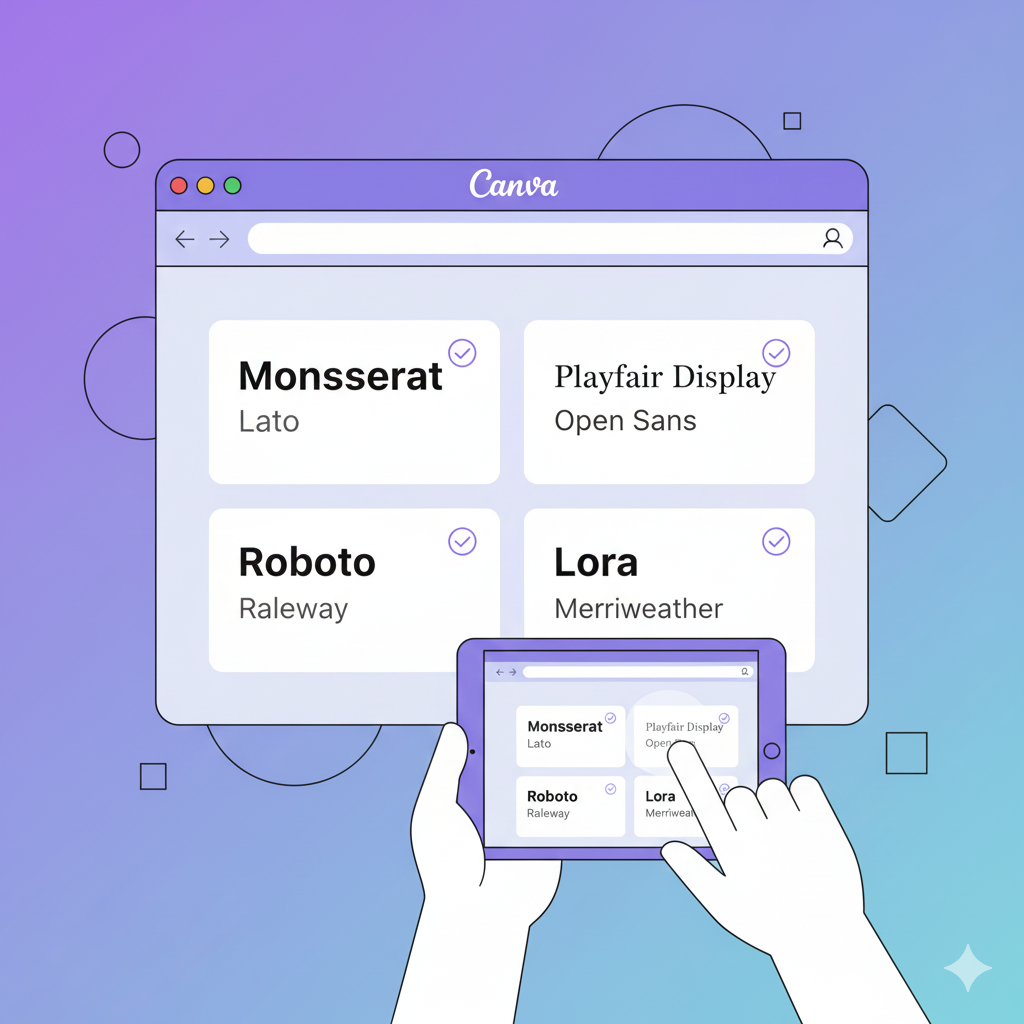
Gubuku – Font memiliki peran besar dalam branding karena secara visual bisa menyampaikan emosi dan karakter bisnis. Misalnya, font tebal dan modern seperti Montserrat memberi kesan profesional dan percaya diri, sedangkan font bergaya tulisan tangan seperti Playlist Script menciptakan kesan personal dan hangat.
Menurut Canva Design School (2024), pemilihan kombinasi font yang baik dapat meningkatkan keterbacaan hingga 40% dan membuat desain tampak lebih harmonis. Kombinasi yang tepat juga membantu audiens mengenali merek hanya dari gaya tulisan yang digunakan.
Jadi, sebelum memilih, pastikan kamu tahu karakter bisnismu: apakah formal, kreatif, ramah, atau elegan? Ini akan membantu menentukan kombinasi font yang paling sesuai.
Prinsip Dasar Mengombinasikan Font di Canva
Sebelum masuk ke contoh kombinasi font, pahami dulu prinsip dasar dalam mengombinasikan font agar hasil desainmu seimbang:
Gunakan maksimal dua jenis font.
Terlalu banyak jenis huruf membuat desain terlihat berantakan. Cukup pilih satu untuk judul dan satu untuk isi teks. -
Kontraskan gaya font.
Kombinasi yang menarik biasanya memiliki perbedaan yang jelas, misalnya antara serif dan sans-serif, atau antara font formal dan kasual. -
Pastikan keterbacaan tetap tinggi.
Walaupun estetika penting, kejelasan teks tetap prioritas utama—terutama untuk materi promosi seperti poster, brosur, atau konten media sosial. -
Sesuaikan dengan identitas brand.
Jika bisnismu bergerak di bidang kreatif, font yang lebih bebas bisa digunakan. Tapi untuk bisnis profesional seperti konsultan atau hukum, font yang bersih dan elegan lebih cocok.
Kombinasi Font Populer Canva untuk Bisnis Profesional
Jika kamu menjalankan bisnis yang ingin terlihat modern, tepercaya, dan profesional, kombinasi berikut bisa menjadi pilihan:
1. Montserrat + Open Sans
Montserrat cocok untuk judul karena tampilannya tegas dan modern.
Open Sans digunakan untuk isi teks karena mudah dibaca di berbagai ukuran layar.
Kombinasi ini banyak digunakan oleh startup teknologi, konsultan bisnis, hingga agensi digital.
2. Lora + Roboto
Lora memiliki sentuhan klasik berkat gaya serif-nya, ideal untuk merek yang ingin tampil elegan tapi tetap modern.
Roboto yang bersih dan minimalis sangat cocok untuk teks pendukung.
Menurut Font Pair (2023), pasangan ini sering dipakai dalam presentasi dan website profesional.
3. Playfair Display + Poppins
Playfair Display menghadirkan nuansa mewah dan feminin.
Poppins memberi keseimbangan dengan bentuk huruf yang bulat dan tegas.
Kombinasi ini cocok untuk bisnis fashion, kosmetik, atau brand personal yang elegan.
Kombinasi Font Canva untuk Bisnis Kreatif dan Online Shop
Bisnis kreatif seperti toko online, usaha handmade, atau brand fashion memerlukan tampilan yang lebih ekspresif. Canva menyediakan banyak font yang bisa mencerminkan karakter unik bisnismu.
1. Raleway + Pacifico
Raleway tampak bersih dan elegan, cocok untuk teks utama.
Pacifico, dengan gaya tulisan tangan yang santai, cocok untuk logo atau headline.
Kombinasi ini menciptakan kesan ramah dan kreatif, sering dipakai oleh brand kuliner dan toko pakaian online.
2. Bebas Neue + Lato
Bebas Neue kuat dan berani, sangat menonjol untuk judul.
Lato lembut dan profesional, menjaga keseimbangan dalam isi teks.
Kombinasi ini populer di dunia desain promosi dan iklan digital (sumber: Canva Fonts Library, 2024).
3. Amatic SC + Josefin Sans
Amatic SC punya karakter unik dan cocok untuk desain yang ingin tampak “handmade”.
Josefin Sans memberi kesan modern agar desain tetap terstruktur.
Ideal untuk bisnis craft, kafe, atau produk rumahan.
Kombinasi Font Canva untuk Bisnis Ramah Alam dan Kesehatan
Bisnis di bidang kesehatan, wellness, atau produk alami membutuhkan kombinasi font yang terlihat tenang, bersih, dan natural.
1. Nunito + Lora
Nunito memiliki bentuk huruf yang lembut dan nyaman dibaca.
Lora menambah sentuhan klasik dan elegan.
Kombinasi ini cocok untuk brand skincare alami atau produk herbal.
2. Quicksand + Playfair Display
Quicksand ringan dan modern, membuat desain terlihat ramah.
Playfair Display memberi kesan elegan pada bagian judul.
Kombinasi ini populer di situs wellness dan yoga (sumber: Canva Community Forum, 2024).
3. Poppins + Raleway
Dua font sans-serif ini terlihat bersih dan rapi, ideal untuk bisnis yang mengedepankan profesionalisme dan minimalisme.
Kombinasi Font Canva untuk Branding dan Logo Bisnis
Jika kamu ingin membuat logo atau identitas brand di Canva, pemilihan font jadi semakin penting karena akan menjadi wajah bisnismu. Berikut kombinasi yang sering digunakan oleh desainer profesional:
Baik kamu menjalankan bisnis profesional, toko online, atau brand kreatif, Canva menyediakan berbagai pilihan kombinasi font yang bisa disesuaikan dengan karakter brand-mu. Dengan memahami prinsip dasar tipografi dan menerapkan kombinasi yang harmonis, desainmu akan terlihat lebih menarik dan berkesan di mata audiens.